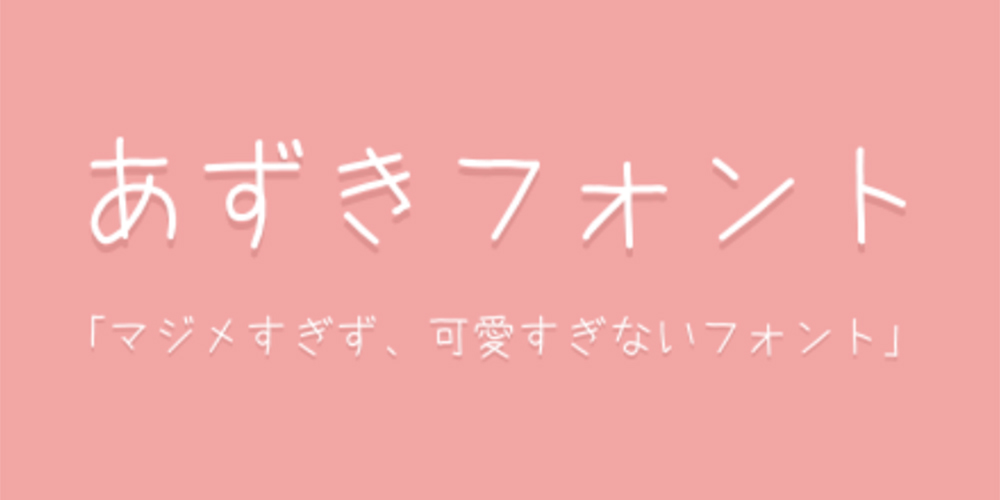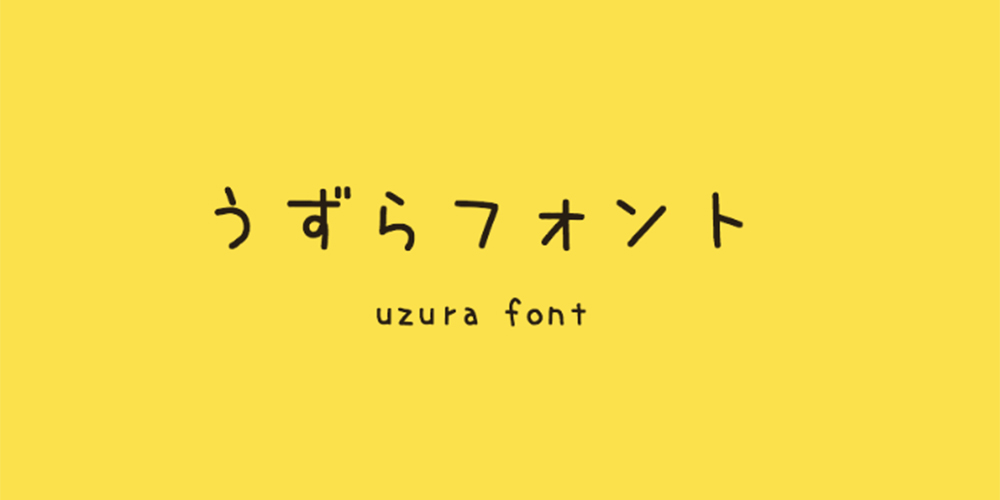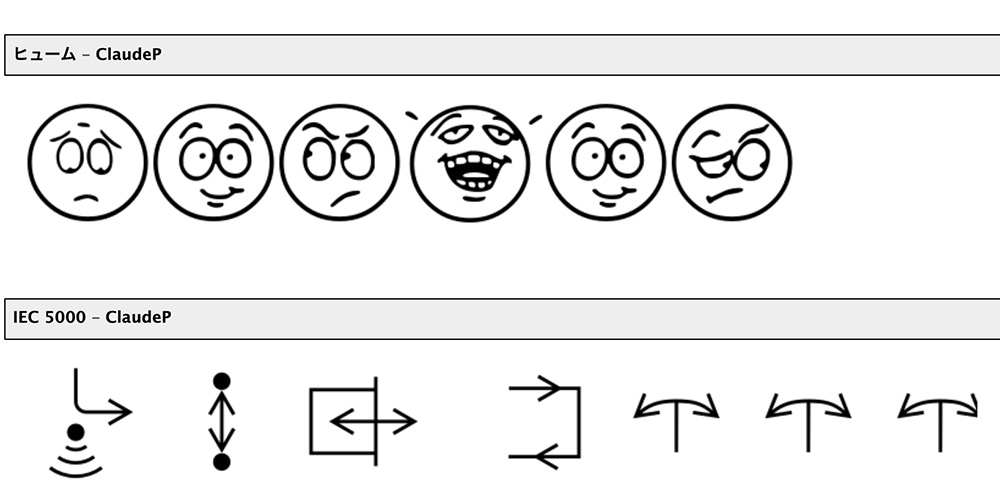
【無料】商用利用OKなフリーフォントが使える 神サイト〜3選〜
商用利用ができるフォント配布サイトを紹介します。頻繁に使えそうなものから、特殊なものまで。英語と日本語のFONTサイトを紹介します。
1.dafont.com
dafont.com
フォントのタイプ毎に探せるので、ある程度使いたいフォントタイプが決まっている時の方が使いやすいかもです。
2.FONT FREE
FONT FREE
日本語のフリーフォントを紹介しているサイトになります。
ゴシック・明朝・手書き風・ポップ体などバリエーションが多いので、困った時はこのサイトを訪れれば何とかなりそうなサイトです。商用可能も数多くあります。
可愛い系のフォントが多い印象です。
3.1001FREE FONTS
1001FREE FONTS
↓特殊なものですと、こんな感じのものもあります。
4.まとめ